Font Gothic Việt hóa là nhóm phông chữ đặc thù mang trong mình hai dòng chảy lịch sử lớn của ngành đồ họa: dòng chữ Blackletter thời Trung Cổ với các đường nét gãy góc mô phỏng vòm nhọn thánh đường châu Âu, và dòng Grotesque Sans-serif hiện đại với cấu trúc khung xương đầm chắc, vững vàng. Với diện mạo uy nghiêm, bí ẩn và giàu tính kiến trúc, tải font chữ Gothic Việt hóa là giải pháp trực quan tuyệt vời để các kiến trúc sư, nhà thiết kế kiến tạo chiều sâu cho các bản vẽ phối cảnh quán rượu hầm container, homestay phong cách cổ điển phương Tây hay các ấn phẩm nhận diện di sản.
Khung sườn gãy góc kiêu hãnh và tính biểu tượng của font Gothic Việt hóa
Điểm cuốn hút của font Gothic Việt hóa nằm ở nghệ thuật tạo hình mang tính kết cấu rõ rệt. Dù ở phong cách Blackletter cổ xưa hay các biến thể hiện đại như All Round Gothic Việt hóa, các con chữ đều sở hữu độ dày nét chắc chắn, tỷ lệ hình học kỷ luật và khả năng chiếm lĩnh không gian hiển thị vượt trội.
Sự ổn định về mặt cảm xúc của dòng font này giúp khơi gợi cảm giác hoài niệm, sự bền vững và chiều sâu văn hóa của công trình. Khi kết hợp cùng các bề mặt vật liệu kiến trúc cổ điển như tường gạch nung rêu phong, đá tự nhiên sẫm màu, gỗ sồi hun khói hay kim loại uốn hoa văn trong các căn nhà lắp ghép cách tân, Gothic tạo nên sự tương thích thẩm mỹ đầy ma mị.
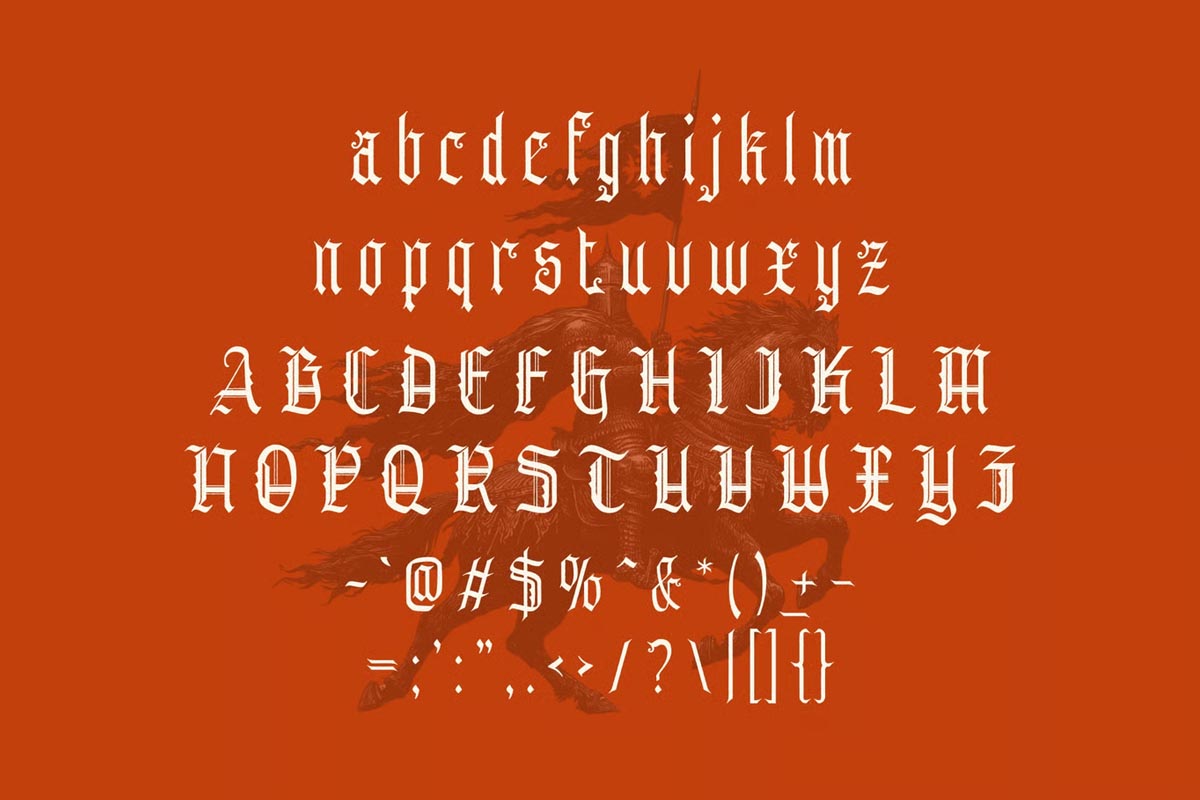
| Phân loại phong cách | Blackletter / Grotesque Sans / Medieval Gothic |
| Nhóm phông tiêu biểu | Old English, All Round Gothic, Cloister Black |
| Mục đích phù hợp | Biển tên quán rượu, logo di sản, bìa hồ sơ kiến trúc |
Tư vấn từ chuyên viên: Font Gothic sở hữu tính biểu tượng thị giác rất mạnh và nhiều đường nét chi tiết. Để bản thiết kế đạt hiệu quả thẩm mỹ tốt, bạn chỉ nên sử dụng phông chữ này cho các tiêu đề chính, tên dự án hoặc khẩu hiệu ngắn.
03 Ứng dụng phông chữ Gothic vào công trình thực tế
Nhờ vẻ ngoài uy nghi và tính gợi cảm xúc mạnh mẽ, bộ phông chữ này mang lại giá trị thực tế lớn trong khâu tạo điểm nhấn cho các công trình hiện đại:
- Biển hiệu cho Quán Bar và Hầm rượu Container: Những nét chữ gãy góc Blackletter rất ăn ý khi gia công chữ nổi bằng đồng thau giả cổ hoặc cắt laser trên sắt tấm phủ sơn tĩnh điện đen mờ, mang lại diện mạo đài các và thu hút khách hàng ghé thăm trải nghiệm.
- Hệ thống biển chỉ dẫn Homestay phong cách Cổ điển: Phông chữ này khi khắc chìm sơn nhũ vàng trên các thanh gỗ lũa hoặc đá tự nhiên sẽ giúp các căn phòng trong khu nhà lắp ghép toát lên chất huyền bí phương Tây, mang lại trải nghiệm nghỉ dưỡng khác biệt.
- Bìa hồ sơ dự án quy hoạch và bảo tồn di sản: Sử dụng font Gothic Việt hóa cho tên dự án giúp tập hồ sơ trông như một tài liệu nghiên cứu chuẩn mực, tạo niềm tin lớn với các chủ đầu tư yêu chuộng phong cách kiến trúc châu Âu.
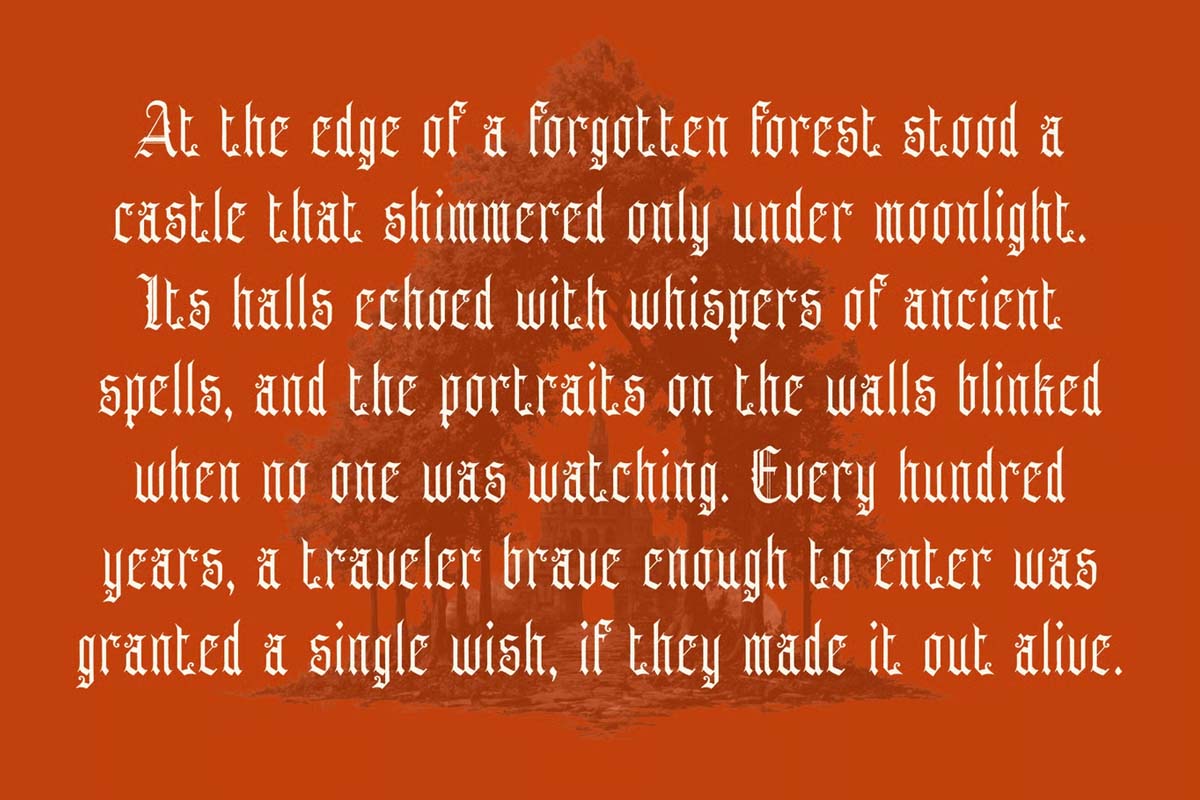
03 Lưu ý bố cục font chữ Gothic giữ trọn chiều sâu thị giác
Để khai thác hiệu quả vẻ đẹp của dòng font kiến trúc cổ điển này mà không gây cảm giác khó đọc cho bản vẽ, người thiết kế nên lưu tâm một số kinh nghiệm sau:
- Tránh viết hoa toàn bộ ký tự ở bản Blackletter: Các ký tự hoa của dòng Gothic thời Trung Cổ có nhiều nét đan cài phức tạp. Việc viết hoa liên tiếp nhiều chữ cái sẽ làm câu văn trở nên khó nhận diện mặt chữ và gây rối rắm bố cục.
- Nới rộng khoảng cách dòng: Do một số nét nhọn của chữ cái có xu hướng vươn cao, bạn nên thiết lập khoảng cách dòng thoáng đãng (khoảng 1.4 – 1.5 lần cỡ chữ) để các con chữ không bị chạm nhau.
- Lựa chọn gam màu trầm cổ kính: Gothic phát huy hiệu quả thị giác cao khi phối cùng các tông màu mang sắc thái bí ẩn như đỏ rượu vang bordeaux, xanh ngọc sẫm, đen tuyền hoặc xám đá tự nhiên trên nền vật liệu nhám mờ.